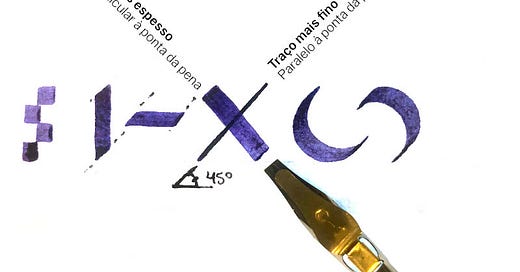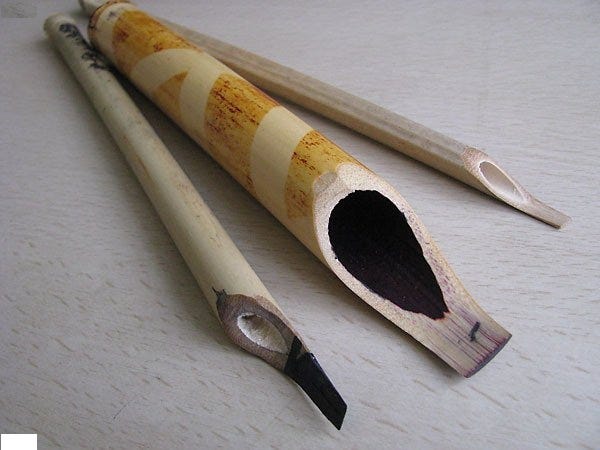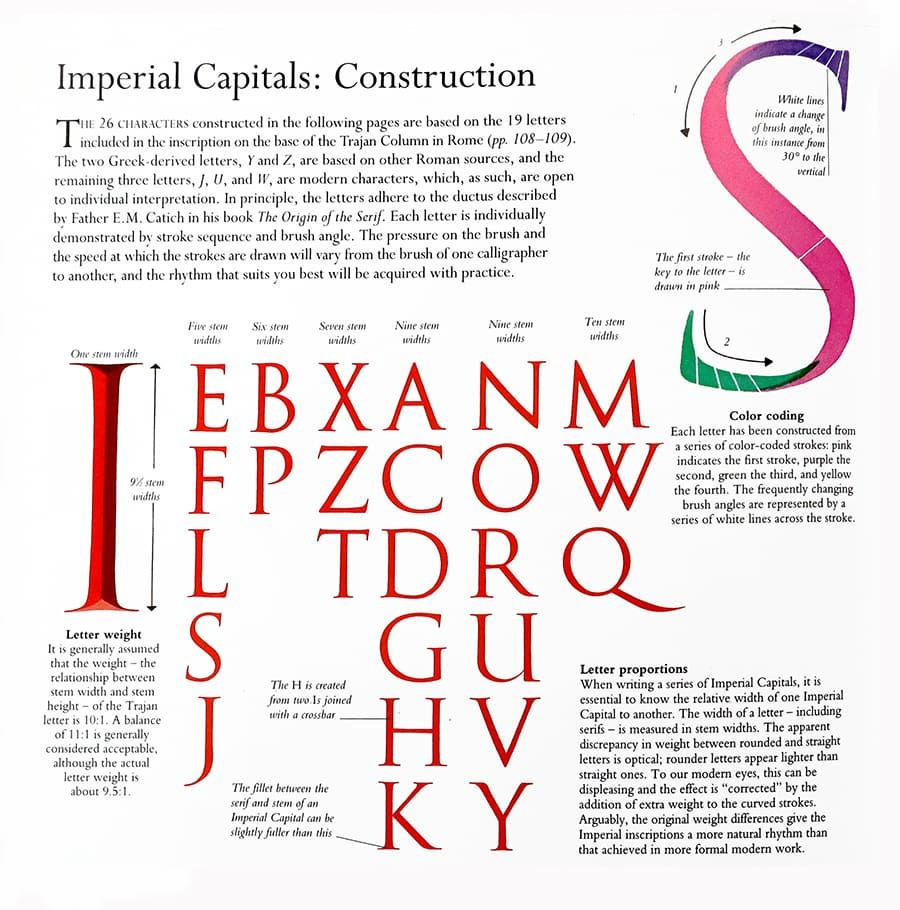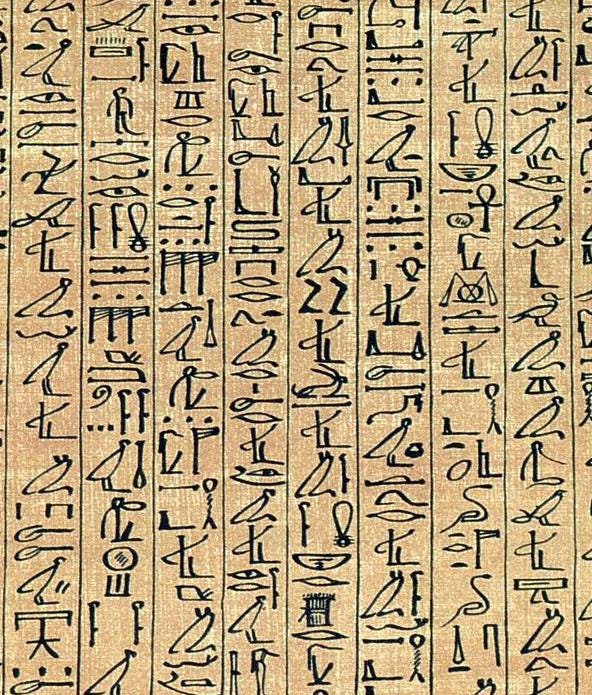
Era para essa edição ser mais uma da TipoAquilo.calt, aquela que eu comecei nesse ano para rodar assuntos mais rápidos, fáceis de tirar do lápis e manter a regularidade. Mais precisamente, seria a inauguração da série “Tipocurso 2000”, para destrinchar tecnicalidades e curiosidades de desenho de letras. Só que, abre uma aba, abre outra aba, e abre mais uma aba, e o conteúdo ficou interessante demais para falar apenas de contraste e ajustes ópticos em tipografia.
Quando alguém pergunta sobre como começar a praticar caligrafia, fazer lettering melhor ou esboçar as primeiras letras da primeira fonte tipográfica, uma pessoa responsável aconselharia a pessoa a estudar e praticar o alfabeto fundamental de Johnston. As letras feitas pelo calígrafo inglês não são tidas como a porta de entrada para drogas mais fortes o mundo das letras à toa: elas exploram, de uma maneira bem iniciática, as virtudes da ferramenta mais fundamental para o exercício e estudo da tipografia. Nesta semana, o Tipo Aquilo presta uma pequena reverência à pena quadrada, e se você ainda não tem, vou tentar te convencer a ter uma. ;)
Tudo mudou para o ser humano quando alguém, mais ou menos 45 mil anos atrás, pegou uma haste molhada com algum pigmento — provavelmente o sangue de seus inimigos — e manchou uma parede com algo que não era só um borrão aleatório. A prática de registrar as atividades e o modo de vida primitivo em desenhos e representações figurativas facilitou a passagem de conhecimento entre gerações cada vez mais distantes umas das outras. Aos poucos, as pessoas dedicadas ao ofício do registro sofisticavam seus instrumentos, adicionando peles de animais para fazer os primeiros pinceis, e talhando algumas partes para melhorar a ergonomia ou fazer estilos de marcação diferentes.
Por ora, atribuímos à civilização egípcia a criação do que entendemos hoje como a pena quadrada. O cálamo era uma haste de bambu ou junco com um corte inclinado que gerava uma ponta, posteriormente afiada e cortada para aumentar a área de contato da pena com o papel — pois é, neste momento histórico já podemos falar de papel. A escrita hieroglífica era usada tanto em pergaminhos de papiro quanto nas paredes de palácios e pirâmides. Ela dispunha de uma versão monumental, utilizada em ambientes e objetos, e uma versão cursiva, utilizada em papel ou madeira. Os hieróglifos cursivos, que deram origem à escrita hierática e demótica, eram feitos com cálamo, e já apresentavam traços com espessuras diferentes, mas que eram todos feitos com o mesmo instrumento.
Para que você possa entender o quanto esse papo de contraste é importante para a tipografia, imagine um carimbo retangular, com largura maior que a altura. Se você arrastar esse carimbo num papel no sentido horizontal, a marca de tinta terá espessura igual à altura. Se você arrasta-lo no sentido vertical, a marca de tinta será mais espessa, da largura do carimbo. Explicando assim, parece até banal, mas esse princípio está presente nos sistemas de escrita desde a antiguidade, e é o que estrutura a teoria da escrita de Noordzij, por exemplo. A ponta retangular do cálamo produzia traços tanto finos quanto espessos, e isso tornava mais ágil o preenchimento de partes específicas de alguns símbolos e a composição de documentos, como um todo.
Os hieróglifos deram origem a quase todos os sistemas de escrita da Europa, África e Oriente Médio; dessa forma, o cálamo e o princípio do contraste também seguiram adiante. Uma das minhas alegrias deste ano foi ver de perto um documento histórico escrito em Ge’ez e notar a presença de contraste em suas letras. Na escrita árabe, o qalam é utilizado até hoje para criar composições caligráficas que usam e abusam do contraste para compôr ritmo e estabelecer uma textura uniforme à peça visual. No mediterrâneo, o cálamo continuou como um instrumento de escrita predominante durante a antiguidade clássica. No Império Romano, o cálamo dividiu espaço com o uso do pincel de ponta chata, e a maleabilidade da ponta desse pincel é fundamental para a criação das letras imperiais e, com elas, as serifas.
Na Idade Média, o cálamo foi substituído aos poucos em escrita de documentos por penas de aves e pontas metálicas — estas, sim, são o que conhecemos popularmente como penas quadradas. As penas de metal ofereciam pontas mais precisas, com contrastes mais acentuados e um controle melhor do fluxo da tinta para a superfície. Por centenas de anos, a pena quadrada foi um instrumento hegemônico para criação de letras, sendo base de todos os estilos caligráficos ocidentais até o séc. XVI. Foram esses modelos caligráficos de pena quadrada que tornaram-se base das primeiras fontes tipográficas: Gutenberg criou seus tipos a partir de letras blackletter, totalmente dependentes da pena quadrada. Jenson, Garamond, Grandjean e outros gravadores de letras, por sua vez, tiveram como base as letras imperiais romanas e a caligrafia humanista, feita com (finja surpresa…) pena quadrada.
Cada modelo caligráfico tem atributos próprios; entre eles, o ângulo que a ponta da pena quadrada forma com a linha de base. Esse ângulo varia comumente de 10˚ a 45˚. A dinâmica da pena quadrada ajuda a explicar, ao menos em fontes serifadas, porque as letras dessas fontes têm traços finos e espessos. O ângulo da pena explica também a presença de eixos inclinados em letras redondas, como o O, C e G. Embora algumas dessas características tenham ficado para trás, à medida que a pena quadrada tornou-se menos comum no desenho de letras, a presença de contraste prevaleceu. Mesmo nas fontes sem serifa, há uma diferença sutil, porém essencial, entre traços finos e espessos.
Foi assim que Napoleão perdeu a guerra que a pena quadrada adquiriu um papel importante no bê-a-bá da tipografia. Entender essa dinâmica do contraste formado pela pena quadrada é fundamental para quem quer desenhar fontes ou fazer lettering tendo os modelos caligráficos medievais e a tipografia moderna como referência. Entender como a pena quadrada funciona é um momento divisor de águas para quem vive de letras, incluindo este que vos fala, porque mesmo que usemos outros instrumentos para desenhar letras que não necessariamente tenham uma ponta chata, a dinâmica da pena quadrada pode ser facilmente reproduzida.
Se isso tudo te parece atrativo, ter uma pena quadrada não é nada inacessível. Existem kit’s prontos com cabo e algumas penas metálicas que podem ser meio caros. Existem também as ruling pens brazucas fenomenais da Dreaming Dogs. Contudo, é possível fazer penas quadradas com insumos baratos. Se você tiver facilidade para conseguir hastes de bambu, pode fazer alguns cálamos. Você pode usar um lápis de marceneiro (aqueles lápis chatos) pra fazer algumas letras. É possível fazer penas quadradas também com lata de refrigerante (veja o vídeo nas recomendações). Aquela dica clássica de prender dois lápis lado-a-lado com elástico também funciona muito bem. Se tudo isso faz seus olhos brilharem, honre os presentes dados à humanidade por Seshat e Thoth, e coloque seu cálamo para trabalhar desde já. ;)
Recomendações:
🎧 Podcast: Academia do Traço #1, em que o calígrafo Nelson Smythe Jr. discorre sobre como começar a praticar caligrafia e desenhar as primeiras letras.
🇧🇷 Fonte brazuca: Quiz, de Lu Leitenperger.